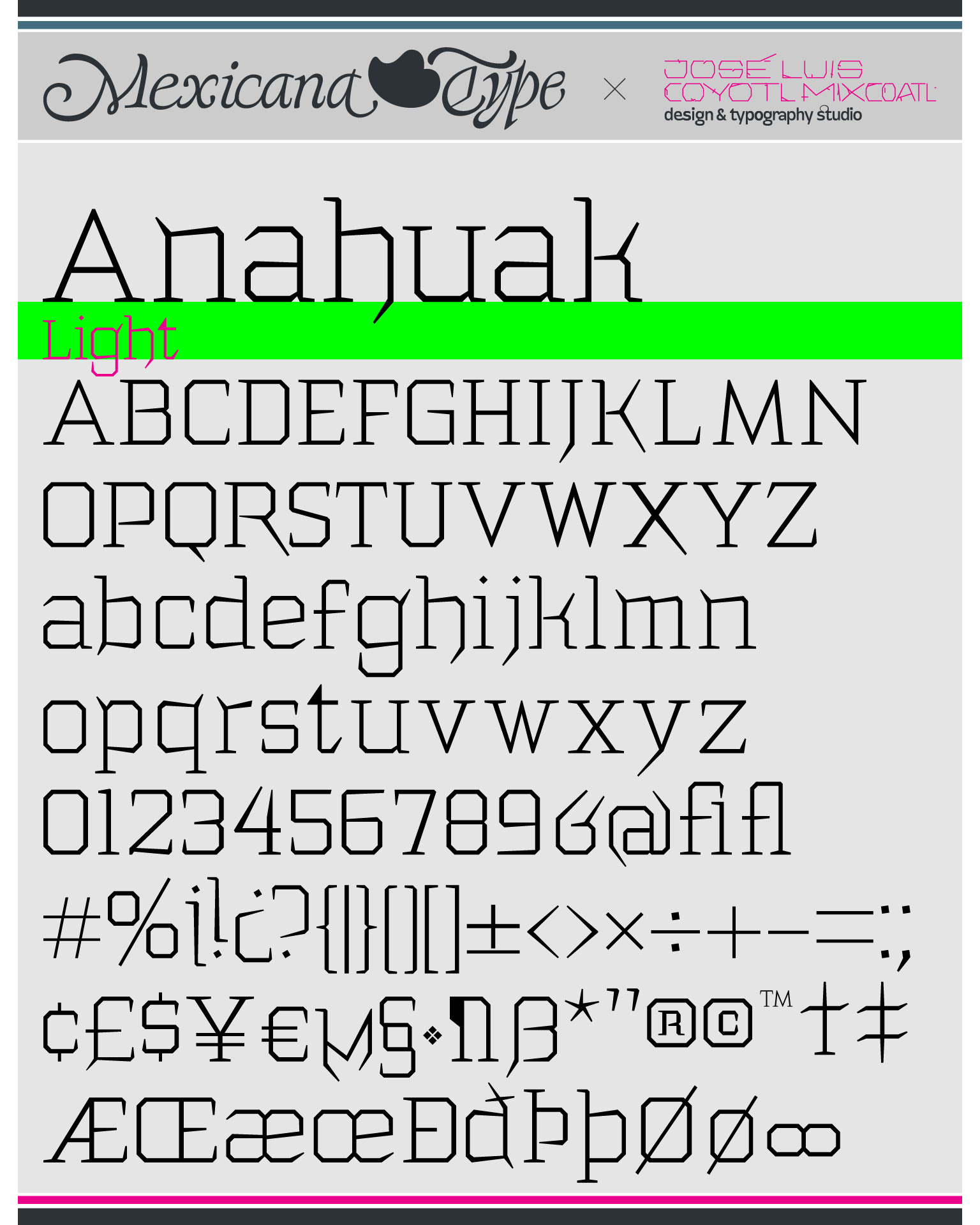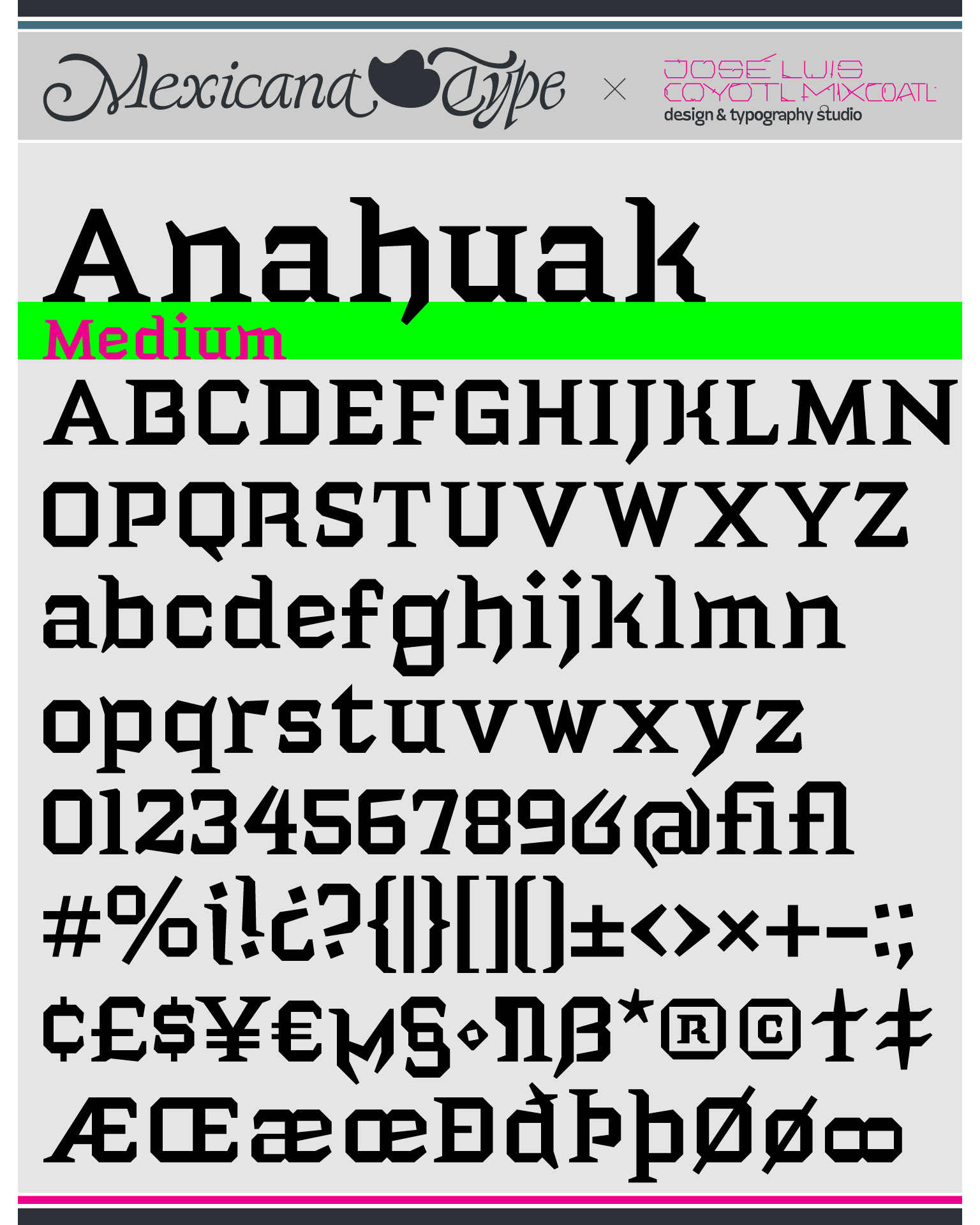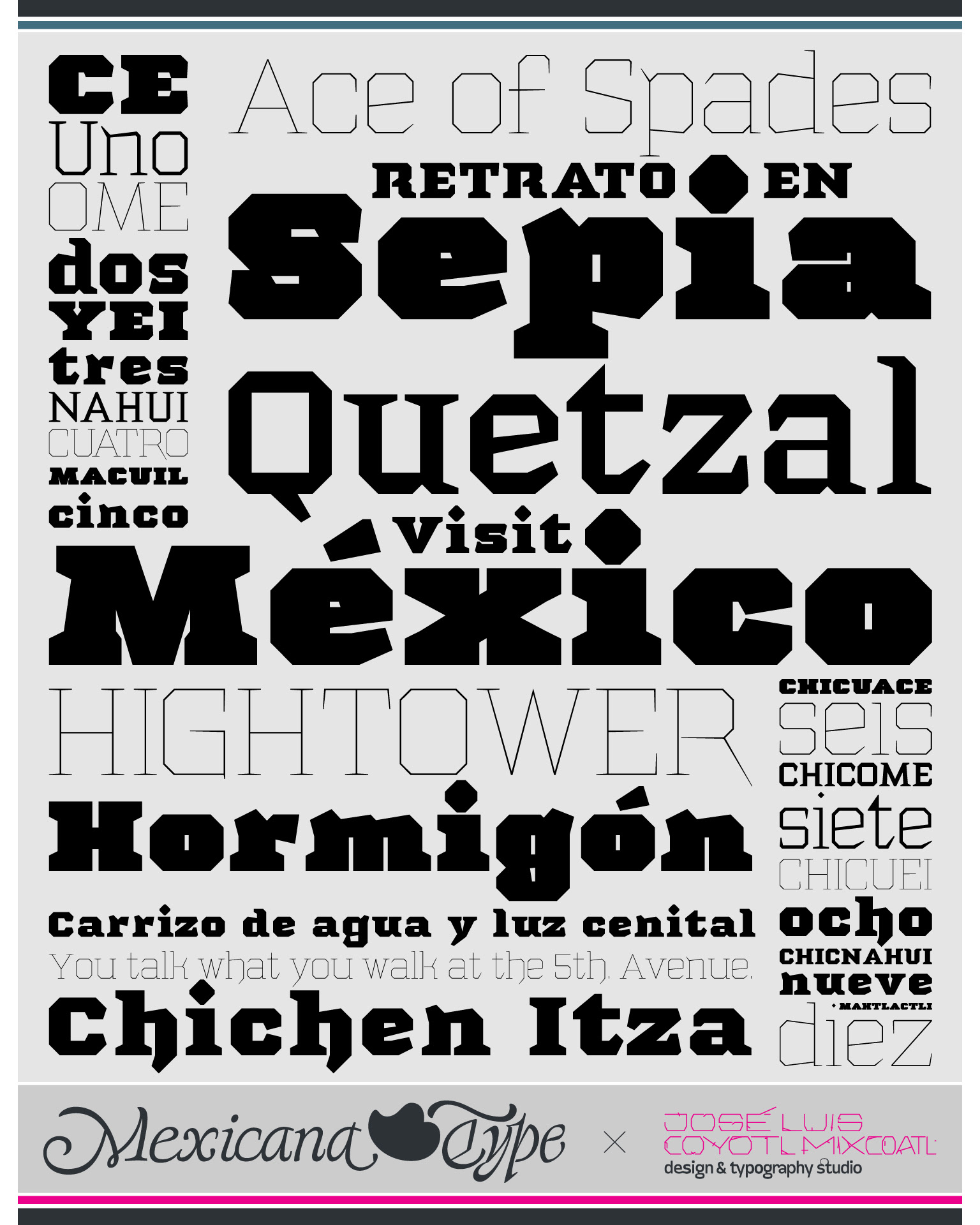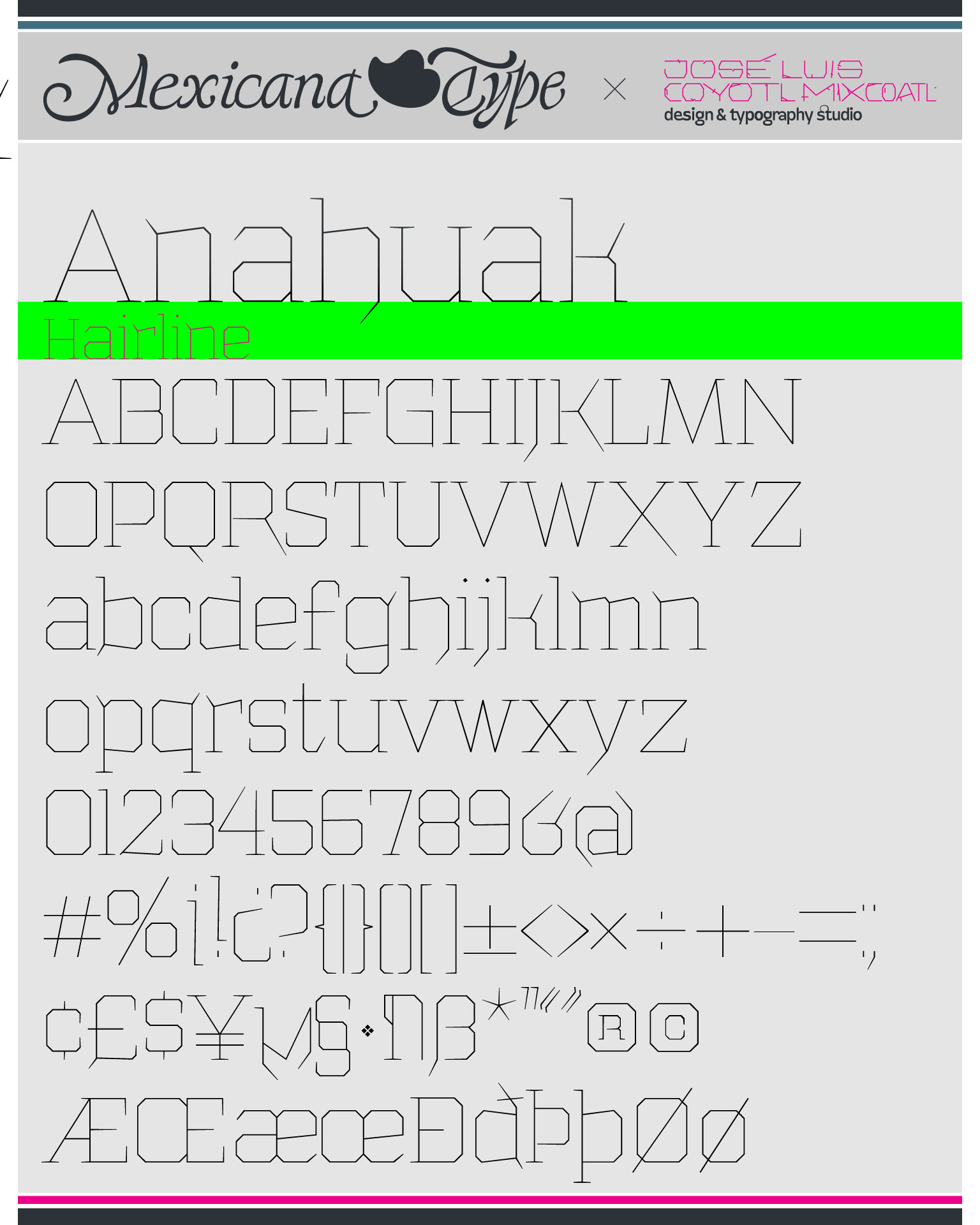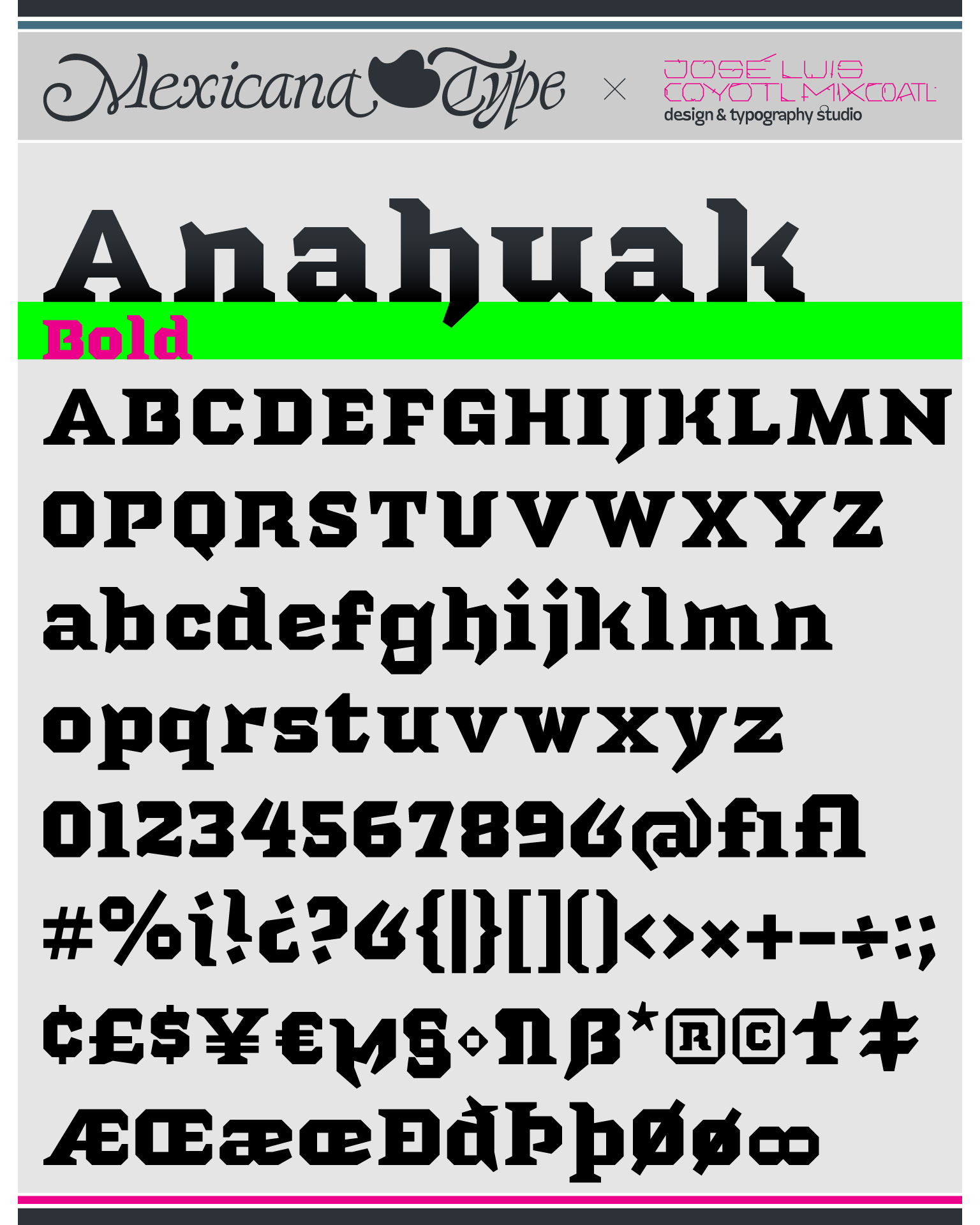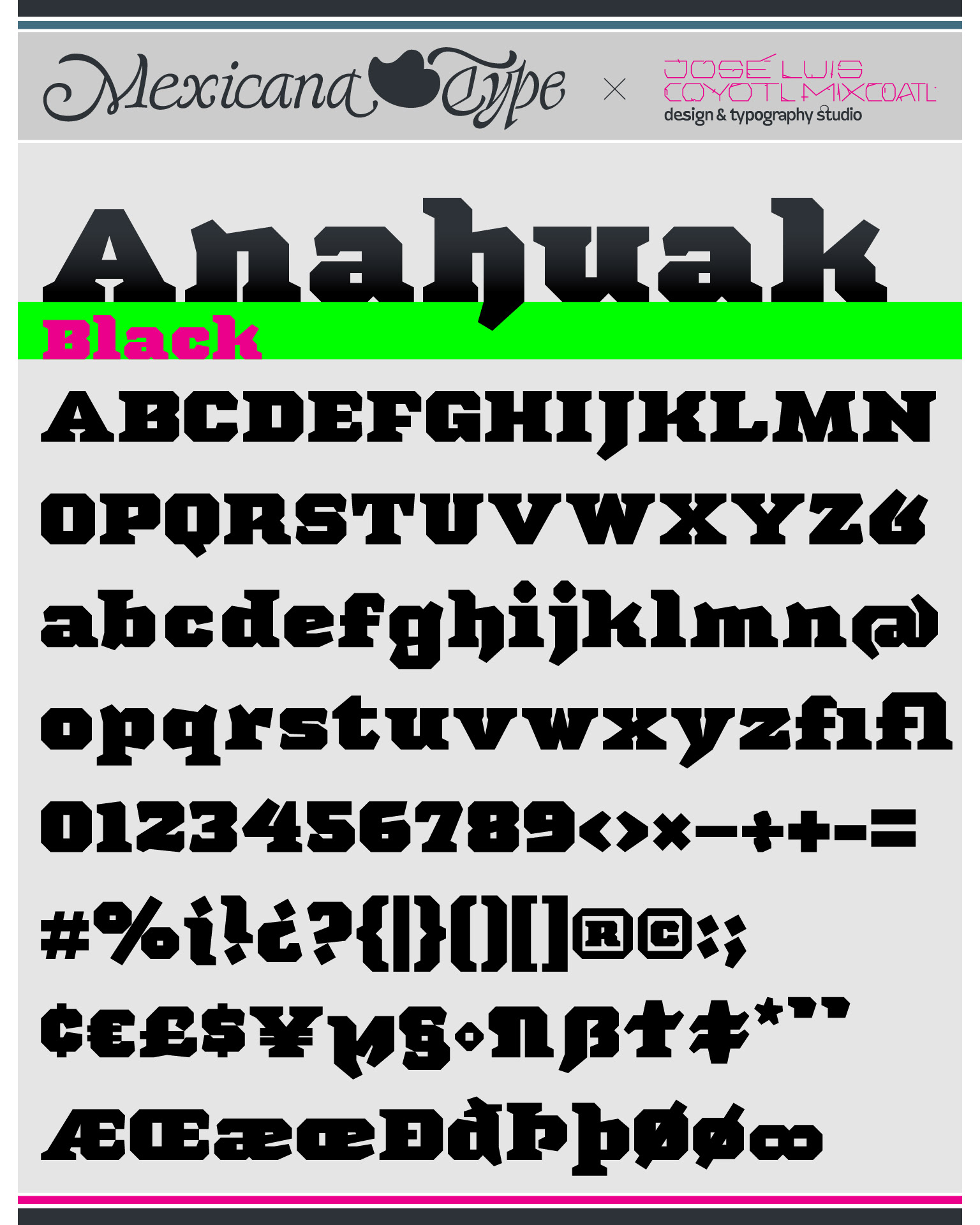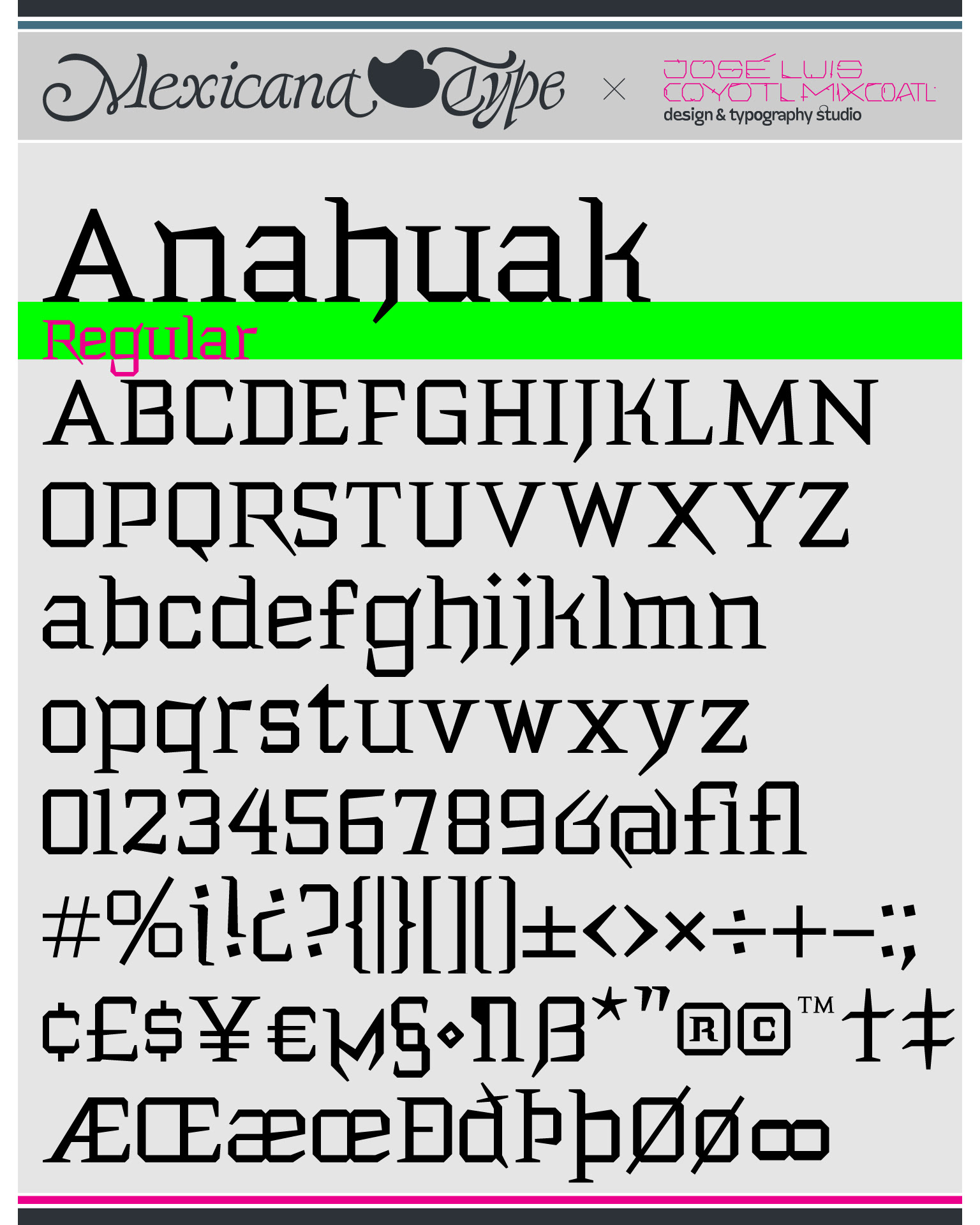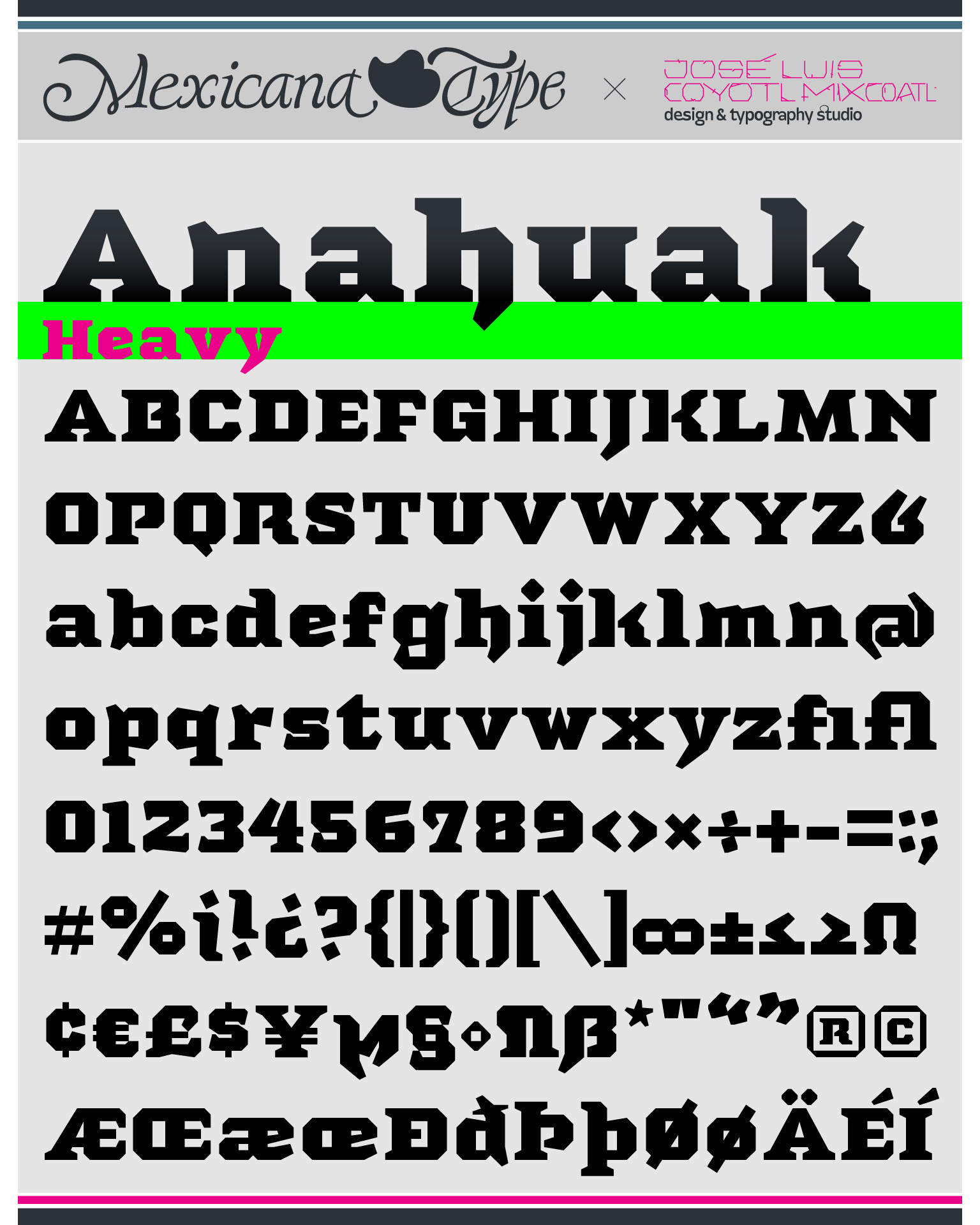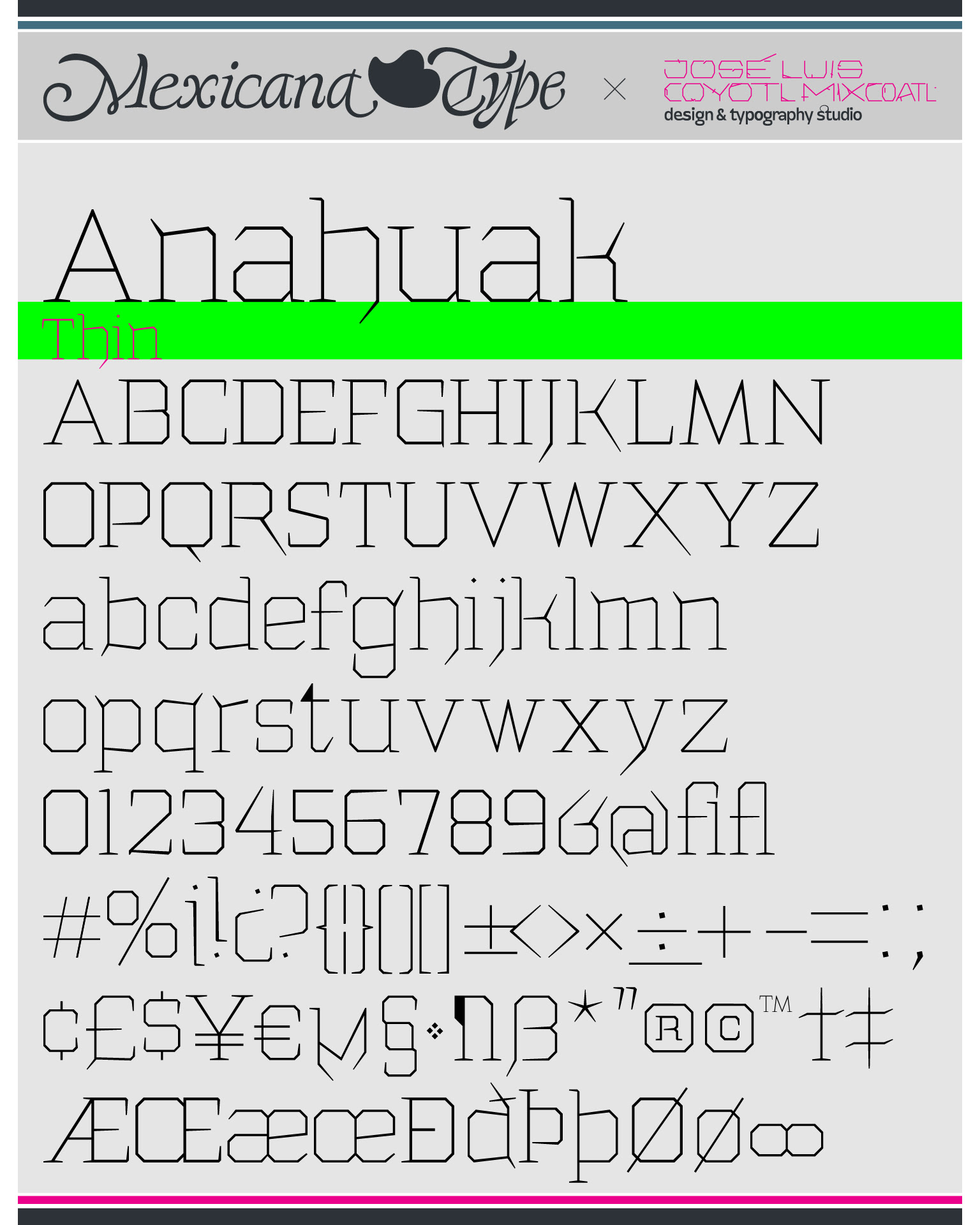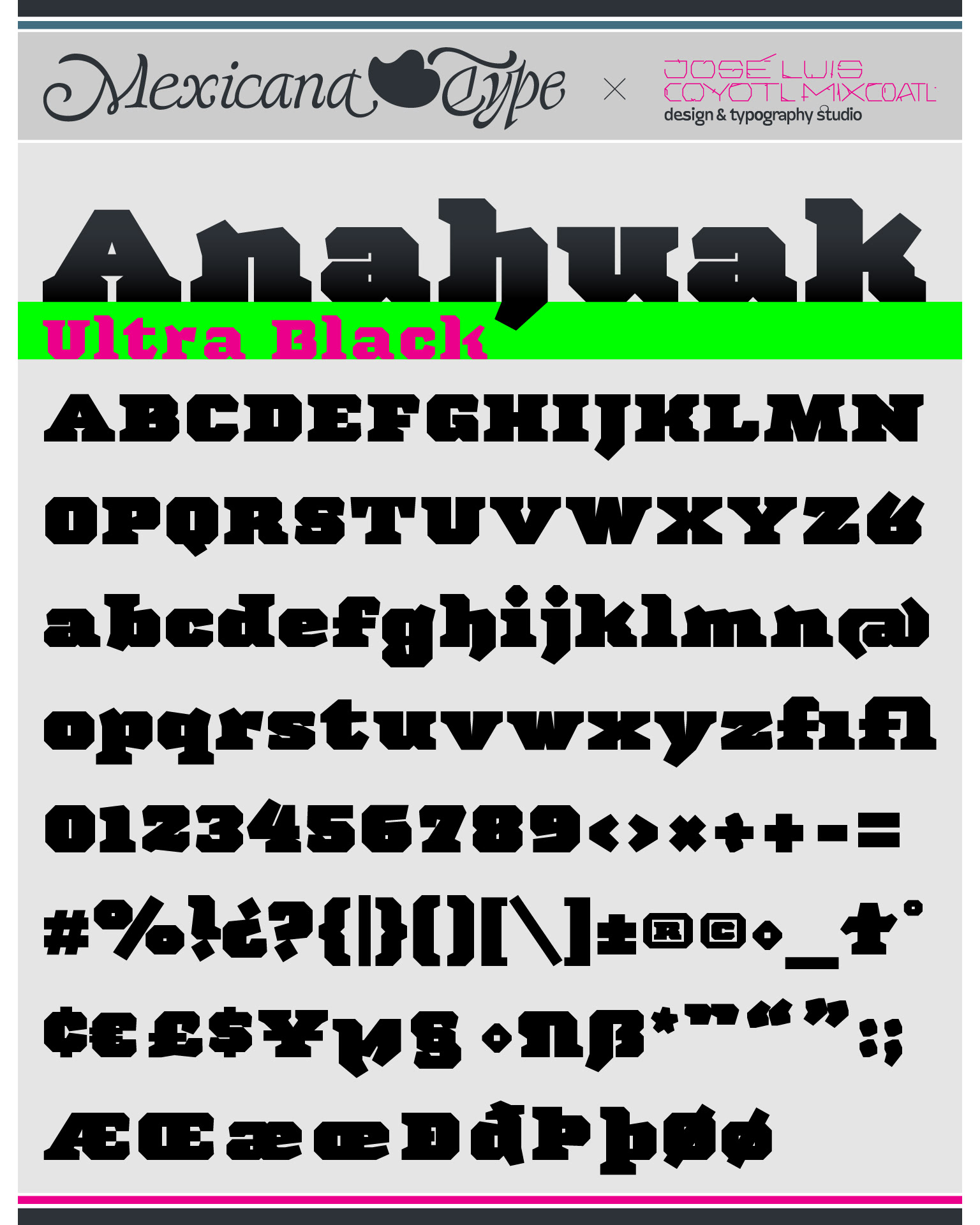
La estructura de MxT Anahuak fue desarrollada a partir de arquitectura prehispánica, particularmente basada en los trazos modulares de muros y pirámides del valle del Anáhuac. Sus líneas son de rasgos sólidos y firmes, con una estructura poligonal en todos sus trazos con rasgos finos pero también elegantes fueron complementados con rasgos de letra negra y serifs firmes y gruesos en la forma de basamentos de la arquitectura precolombina y colonial, con un rango amplio de pesos tipográficos lo cual la hace una familia muy versátil para títulos especialmente.